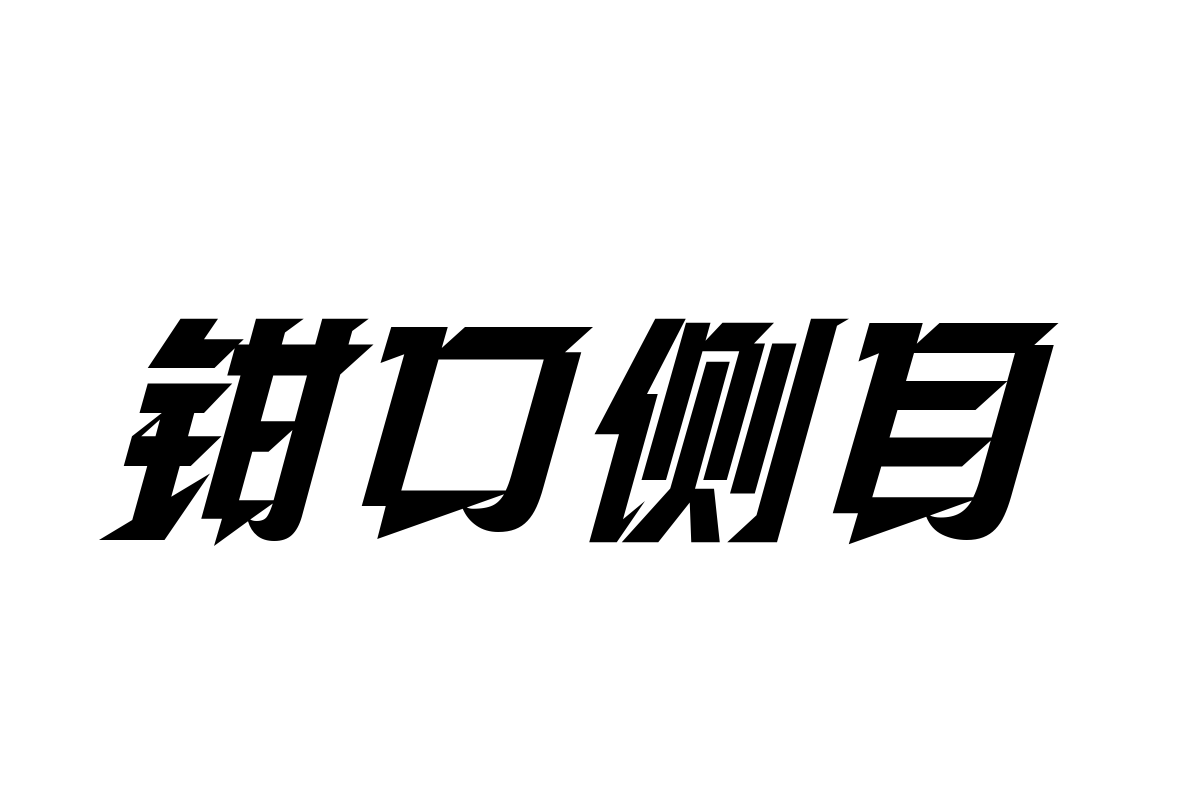
汉仪疾风字体是一款免费商用的中文简体无衬线字体,由汉仪字库出品。该字体具有现代、简约、时尚的特点,适合用于各种商业、广告、设计等领域。
汉仪疾风字体的特点如下:
1. 简洁明了:字体线条流畅,没有多余的装饰,使得整体看起来更加简洁大方。
2. 易读性强:字体笔画粗细适中,间距均匀,使得文字阅读起来更加清晰易懂。
3. 适应性强:适用于各种印刷和电子媒体,如报纸、杂志、书籍、网页等。